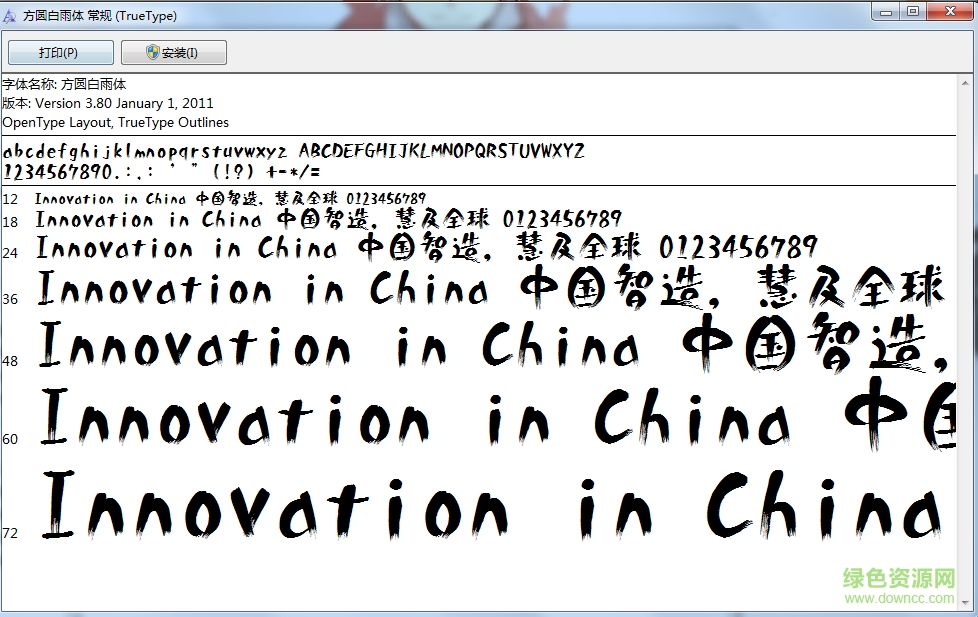
fybyt字體又叫方圓白雨體,是一款字形獨特的書法字體,點墨飛揚,灑脫靈動,非常漂亮,小編還為大家整理了批量安裝字體的方法,需要的小伙伴快來下載吧!
字形的特點活潑自由、顯示風(fēng)格個性,書法體的設(shè)計雖然很有個性、很美觀,但識別性差,用于標識設(shè)計時的不常見,常見的情況是用于人名,或非常簡短的商品名稱。